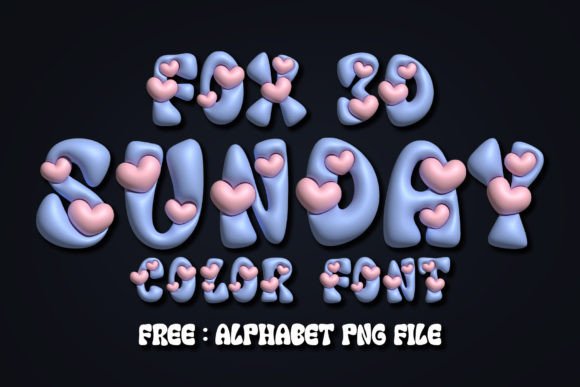
Fox Sunday 3d
Fox Sunday 3d gibi yüksek kaliteli varlıklar arıyorsanız, bu premium paket yaratıcı projeleriniz için harika bir seçimdir.
İster İsteğe Bağlı Baskı (POD) ürünleri, ister düğün davetiyeleri veya sosyal medya grafikleri oluşturuyor olun, Fox Sunday 3d ideal bir uyumdur.